Jason Smith, fundador y exdirector de la fundición tipográfica Fontsmith, ha creado una aplicación que ayuda a transmitir mensajes tipográficos de forma fácil y sencilla. La app se llama Wordilly y ya está disponible en Apple Store.
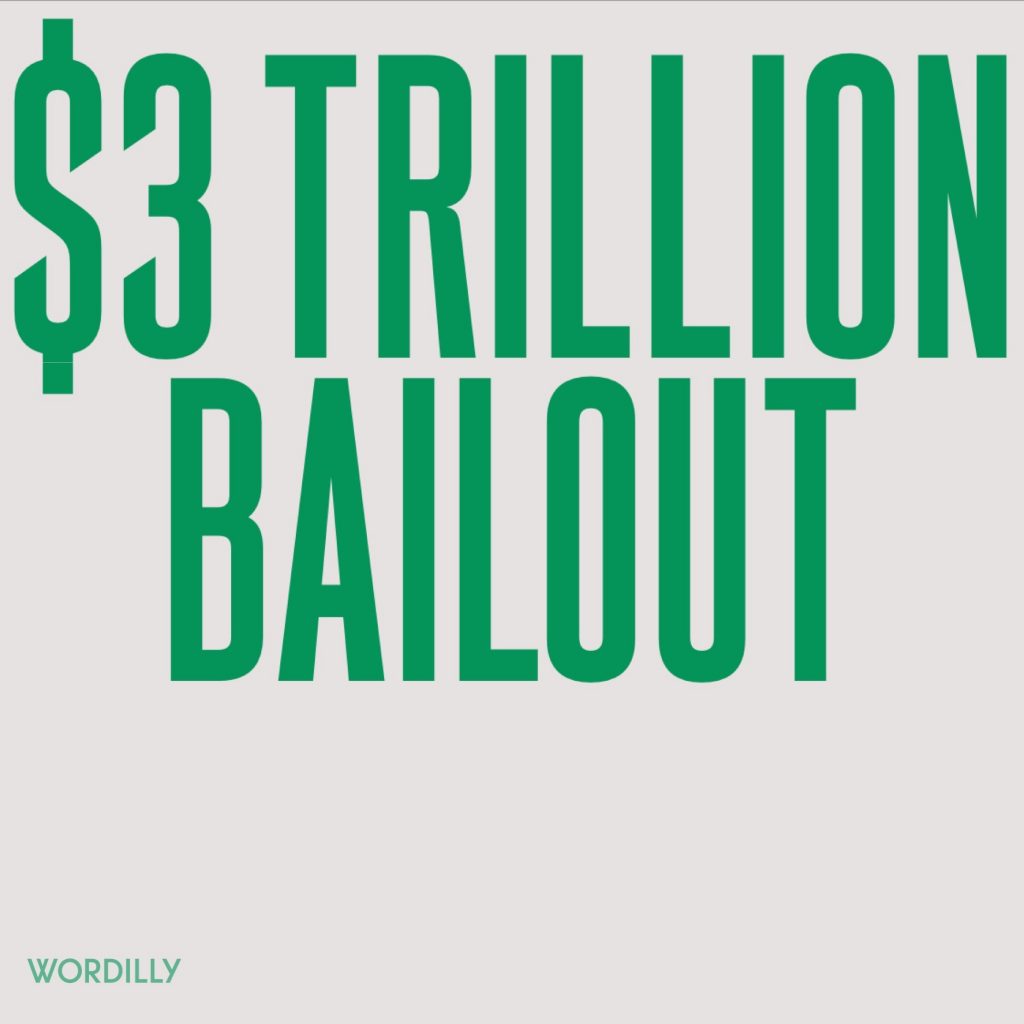
Tras la venta de Fontsmith a Monotype, Jason Smith decidió que tenía que dejar el negocio por un tiempo y dedicarse a otros trabajos diferentes. Fruto de este periodo de descanso y reflexión ha nacido Wordilly, una aplicación en la que Smith llevaba pensando mucho tiempo y que ayuda a los usuarios a comunicar de una manera más eficiente lo que deseen a través del protagonismo indiscutible de la tipografía.
El objetivo de la aplicación es facilitar a los usuarios el poder diseñar mensajes originales y con diseños de calidad para publicar en sus redes sociales o compartir con sus amigos y familiares.
Wordilly permite elegir entre 20 tipografías diferentes (en negrita, cursiva; serif, san serif...), todas ellas de la librería de Fontsmith, y 20 colores que facilitan muchas combinaciones que se adaptan a la situación del mensaje. Además, la interfaz intuitiva de la app elige el diseño y el texto según sus condiciones. El resultado final es una foto que puedes compartir fácilmente a través de las redes sociales.
La aplicación es fruto del trabajo de dos años de Jason Smith, y otros dos creativos. Cuentan que desde siempre han creado mensajes rudimentarios para publicarlos en sus redes sociales, y pensaban que sería muy útil crear una aplicación que facilitara y agilizara la creación de este tipo de mensajes.
Poemas, cartas de amor, chistes o críticas… Wordilly coge tus palabras y les da la forma y el diseño adecuado.